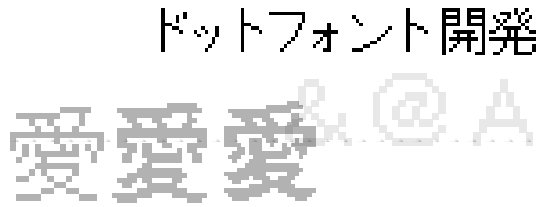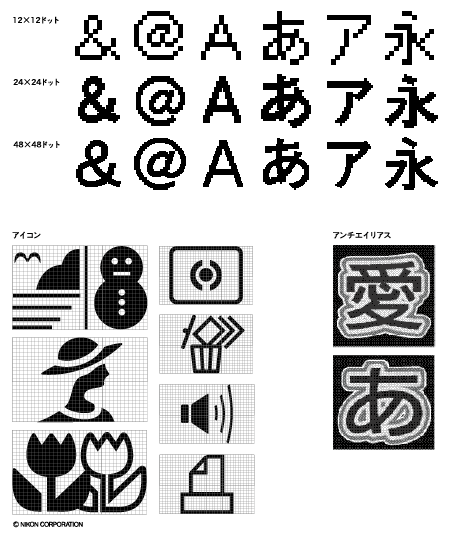
ドットフォント
携帯端末・デジカメ・ゲームソフト・PDA・計測器などにご使用いただくため、ドットフォントを豊富に取り揃えています。明朝体/ゴシック体を始め教科書体、丸ゴシック体、隷書体など多くの書体が揃っています。また、中国語(簡体・繁体)、韓国語のフォントもあります。
2値化フォント以外に輪郭のドットが目立たないグレースケールフォント、アンチエイリアスフォントのご提供もできます。
【ドットサイズ見本】